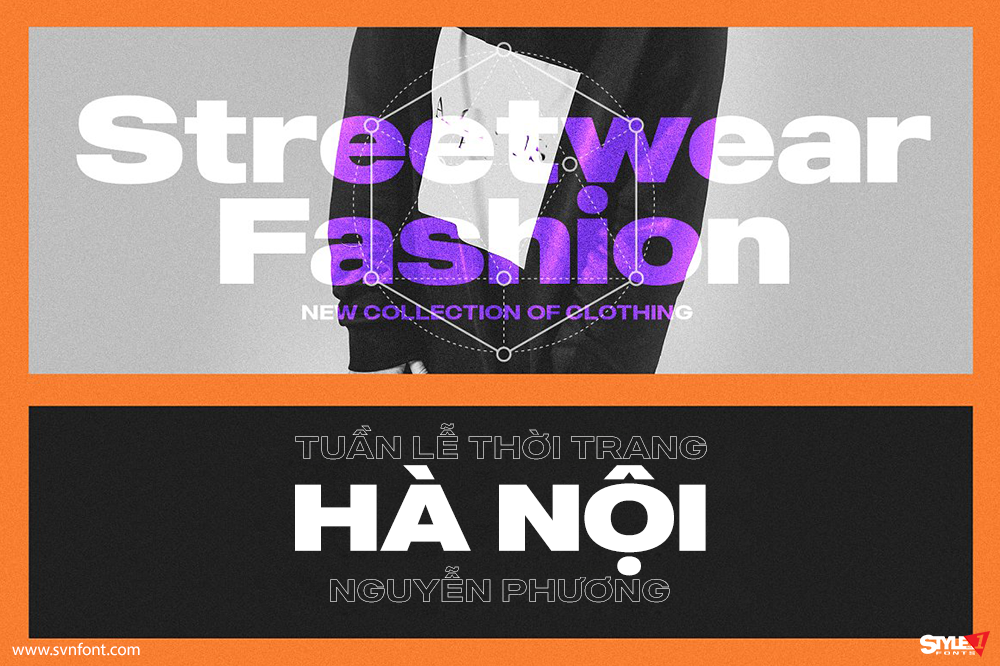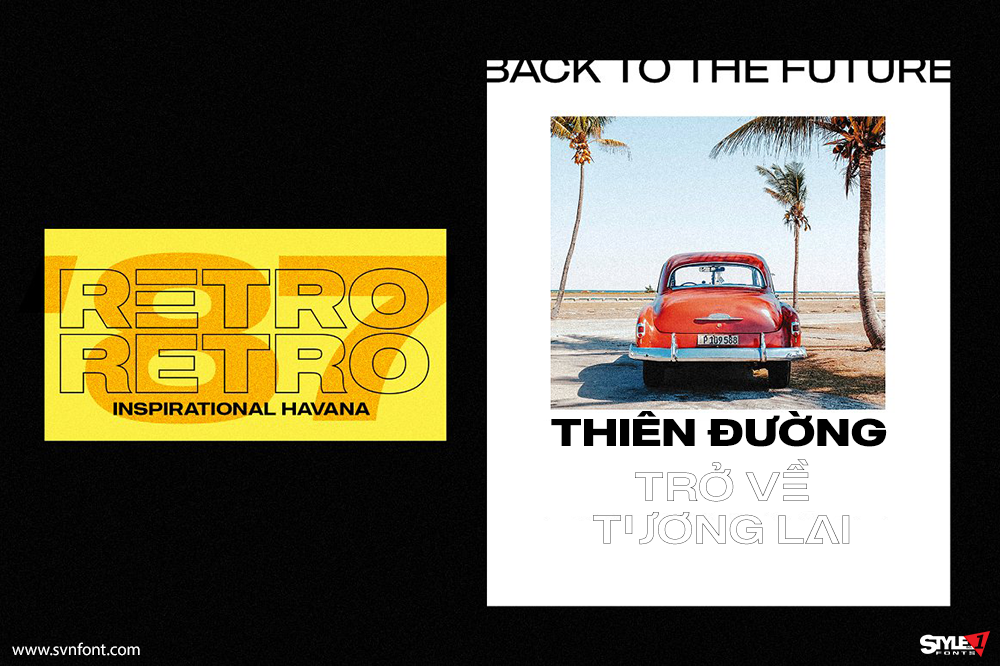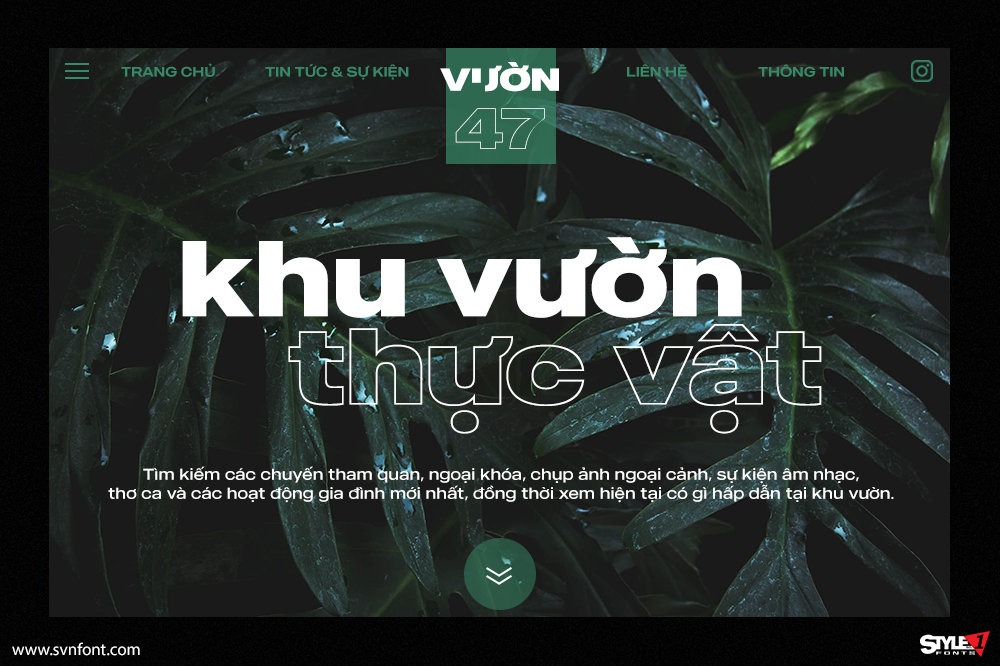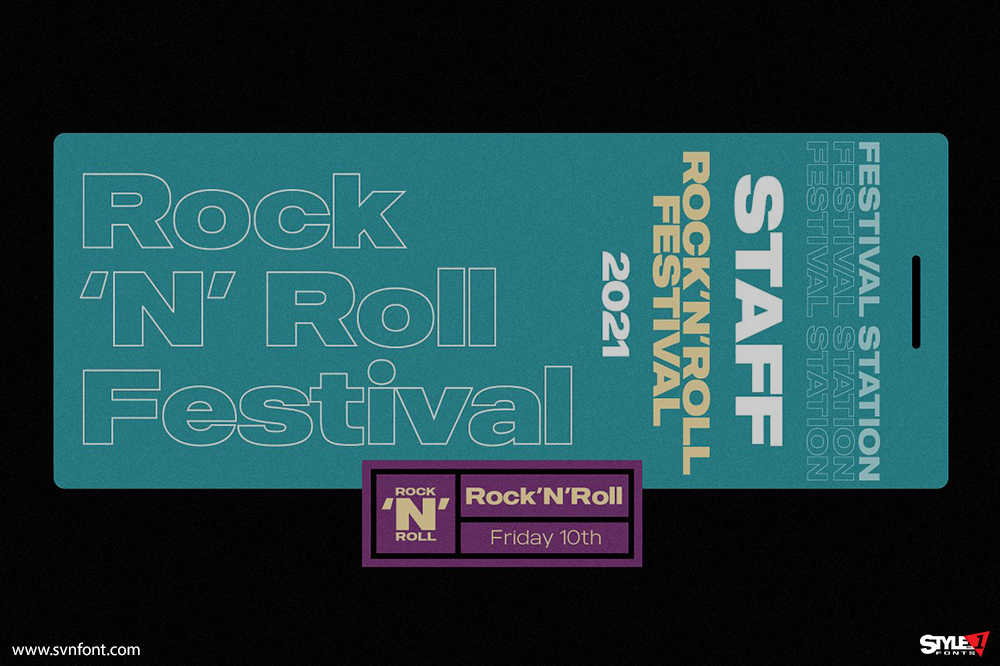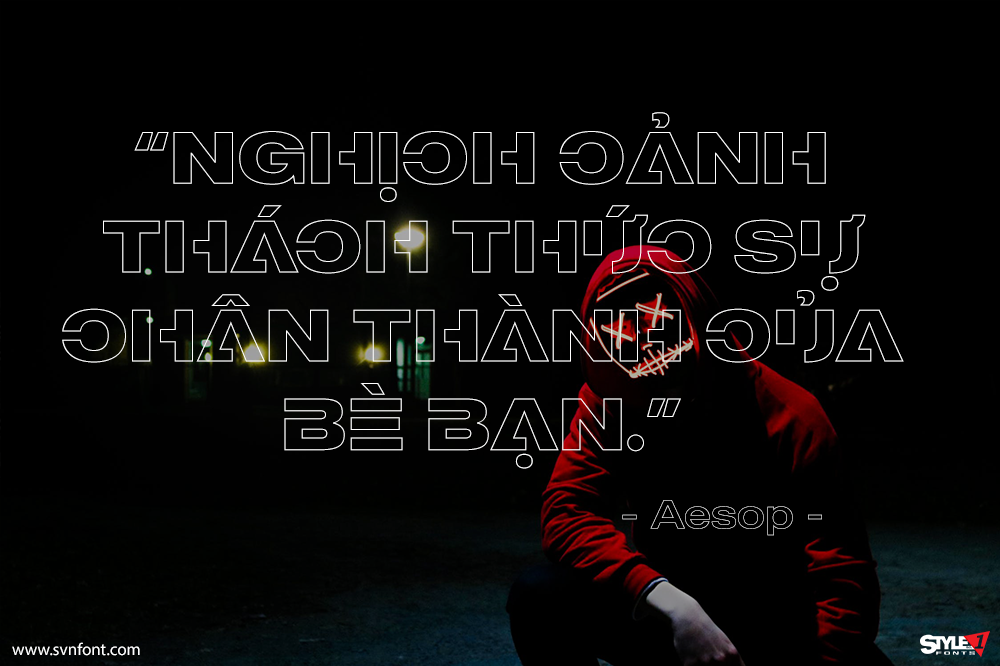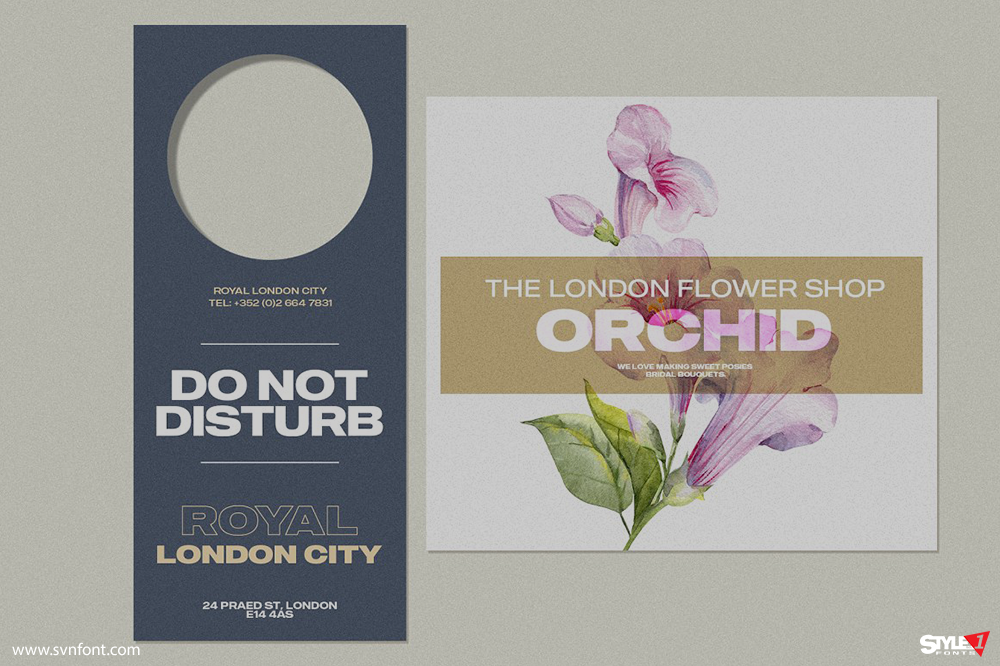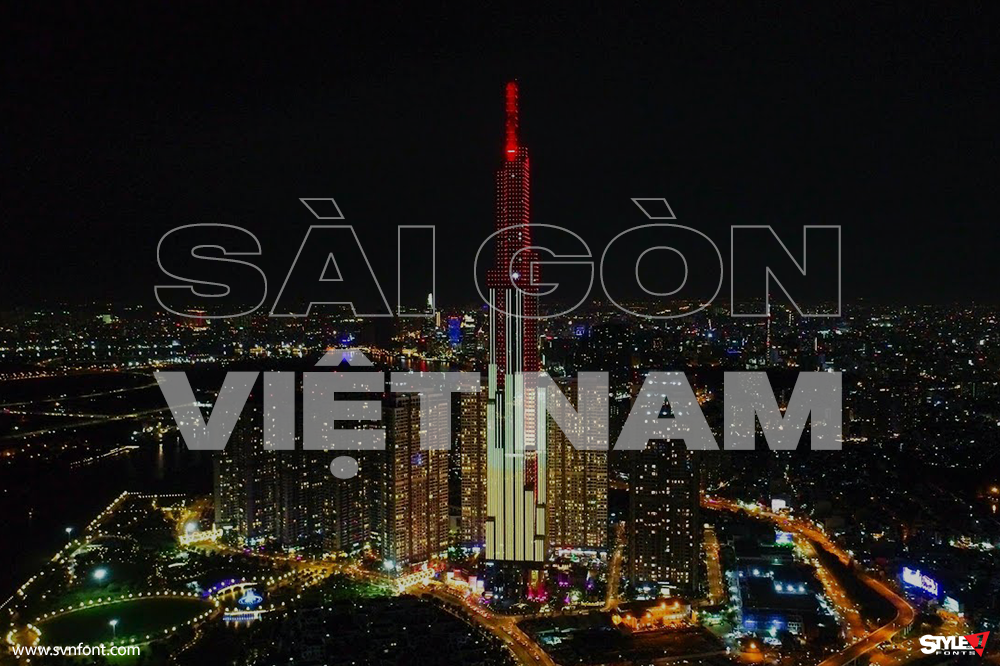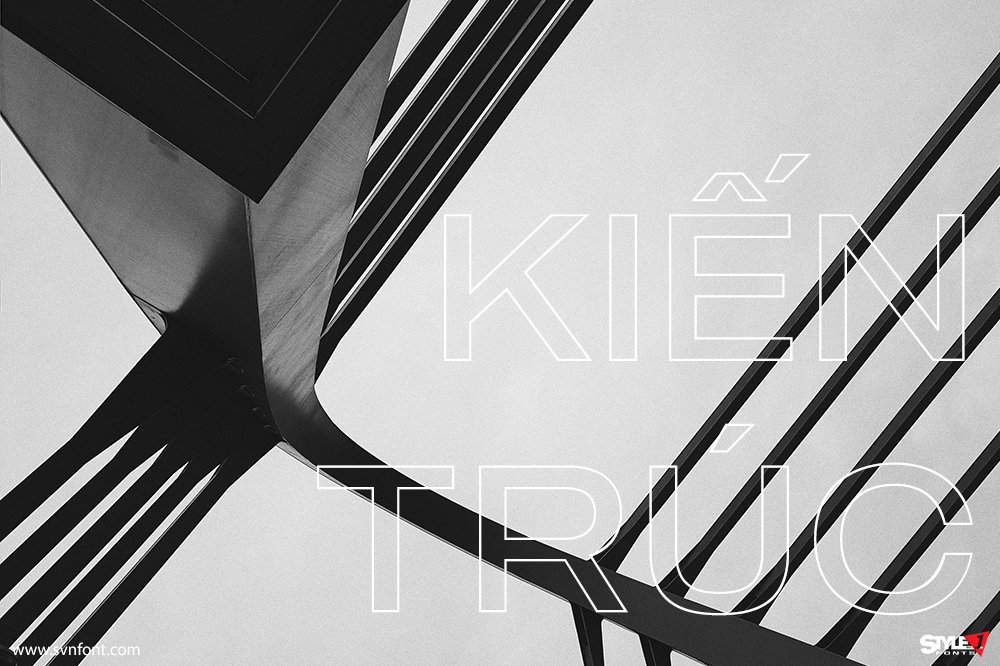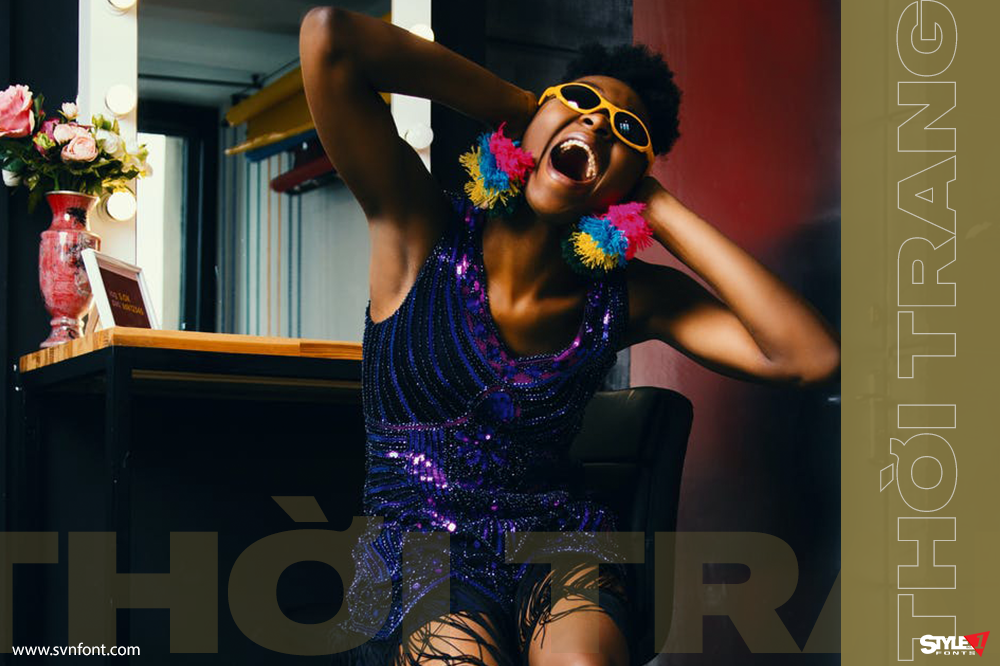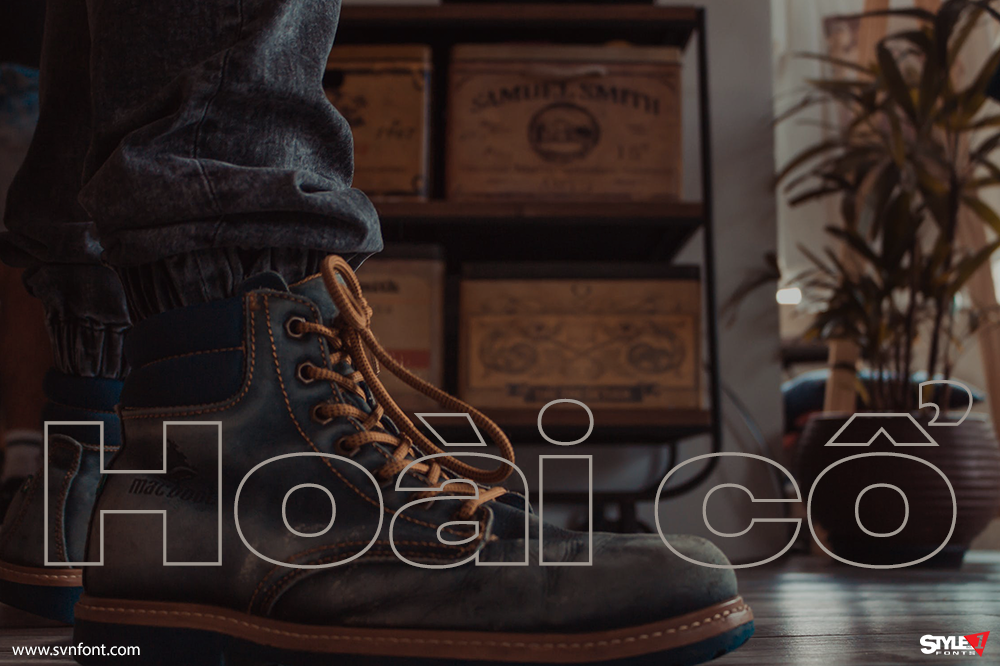
MADE Outer Sans là một bộ phông chữ hiện đại gồm 24 kiểu. Bộ phông chữ Outer Sans sẽ hoàn hảo cho nhiều dự án: thời trang, thiệp mời, bìa nhạc, poster game, rạp chiếu phim, sách, tạp chí, logo, xây dựng thương hiệu, nhiếp ảnh, thiệp cưới, trích dẫn, tiêu đề blog, poster, quảng cáo, áo phông, v.v.
*Bộ font gốc gồm 24 styles trong đó có 12 styles là kiểu thay thế đối với chữ in hoa của các ký tự: A, B, C, D, E, F, G, H, J, K, P, Q, R, U, Y. Bản Việt hóa mình gộp lại thành 12 styles, hỗ trợ ký tự thay thế tiếng Việt.